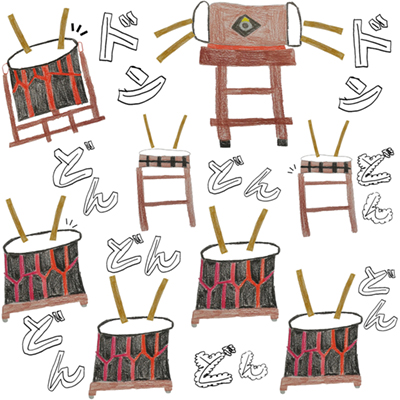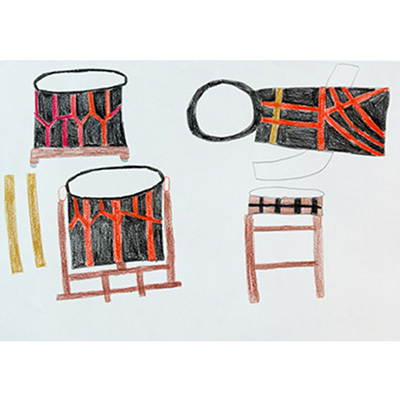
太鼓
太鼓は楽しいよ!
Artist安田直樹
DesignerPirika*design
Organizationあそ美
お祭り大好き、太鼓が特に好き。(安田直樹)
安田さんは和太鼓が好きで、そのエピソードをいつも楽しそうに話してくれます。それぞれの大きさの太鼓に合わせて色んな“どん”の文字を実際に鳴っているかのように臨場感溢れるかたちに仕上げました。イベントグッズにもおすすめです。(Pirika*design)
安田さんは地元の太鼓団体が大好きで、イベント毎について行っています。そんな思いから、このパターンが完成しました。(あそ美)